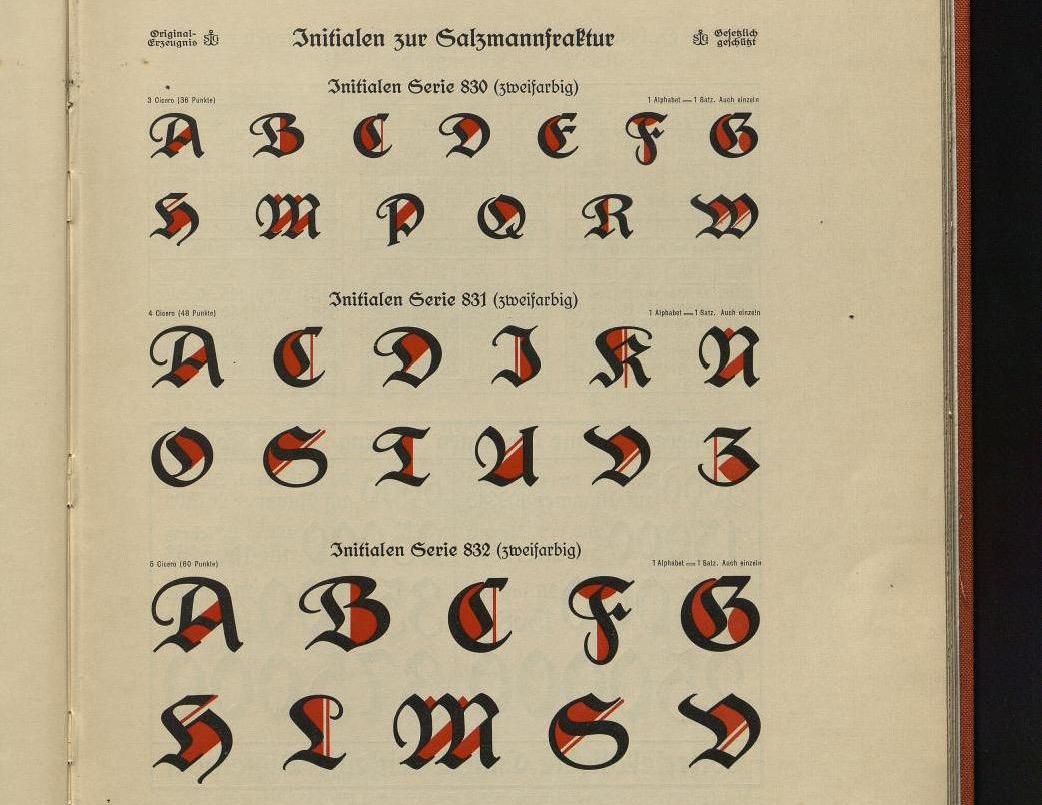
- 1909
- Gebrochene Schrift
Die Salzmann-Fraktur von Max Salzmann erschien ab 1909 bei der Schriftgießerei Schelter & Giesecke und wurde in der Folge weiter ausgebaut. Schlussendlich bestand die Familie aus den Schnitten mager, kräftig, fett, schmal und schmalhalbfett. Zweifarbig einsetzbare Initialen waren ebenfalls erhältlich.